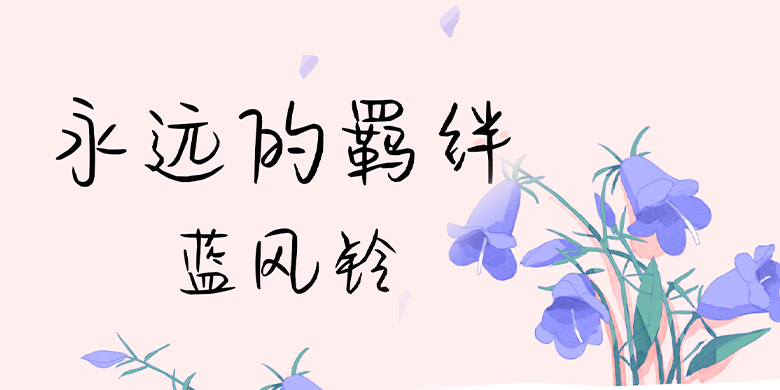
方正手迹-永远的羁绊蓝风
字体品牌: 方正手迹 设计师:宋昱东 字体分类:创意书写 字体属性:精品字 字符集:简繁扩展(GBK) 发布时间: 2020
永远的羁绊-蓝风铃是一款风格鲜明的手写体。该字体整体视觉瘦高,重心考上,是的字体高挑优雅,笔画圆润光滑,转折流畅体现出字体的有趣。该字体适用于文艺类的书刊、品牌广告和产品包装设计,以及社交网络的个性化用字。